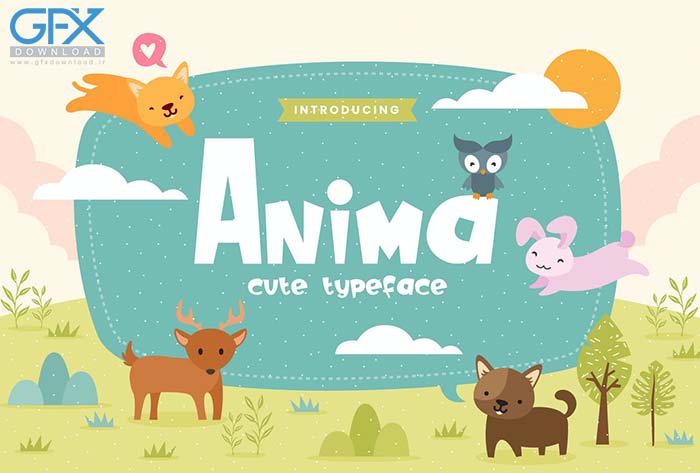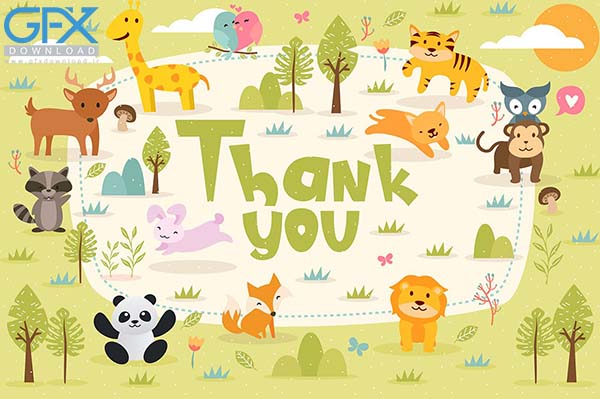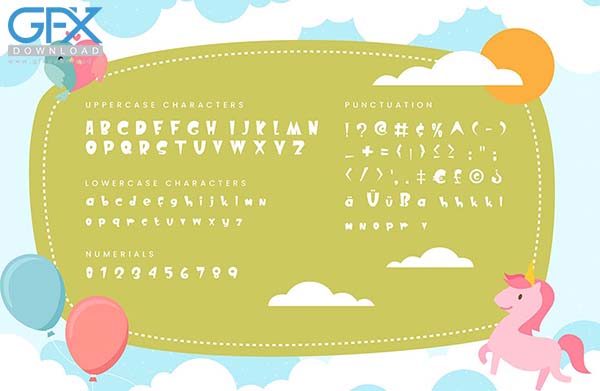
دانلود رایگان فونت فانتزی کودکان Anima
دانلود رایگان فونت انگلیسی فانتزی برای طراحی های کودکانه
آیا به دنبال یک فونت جسورانه و سرگرم کننده برای کودکان هستید؟ فونت آنیما Anima مناسب انواع طراحی های کودکان شامل آلبوم کودک،بنر،کارت دعوت تولد کودکان و سایر طراحی های کودکانه دیگر می باشد.این فونت انگلیسی فانتزی کودکانه به همراه 10 کاراکتر وکتور حیوانات عرضه می شود که می توانید تمامی این ها را به صورت کاملا رایگان در جی اف ایکس دانلود دریافت نمایید.اگر به دنبال فونت مناسب برای استفاده در اهداف ویژه مناسبت های مربوط به کودکان هستید حتما از فونت آنیما Anima استفاده نمایید.
• حروف انگلیسی بزرگ و کوچک از a تا z
• اعداد
• نشانه گذاری ها
• 10 کاراکتر وکتور حیوانات برای طراحی های کودکانه